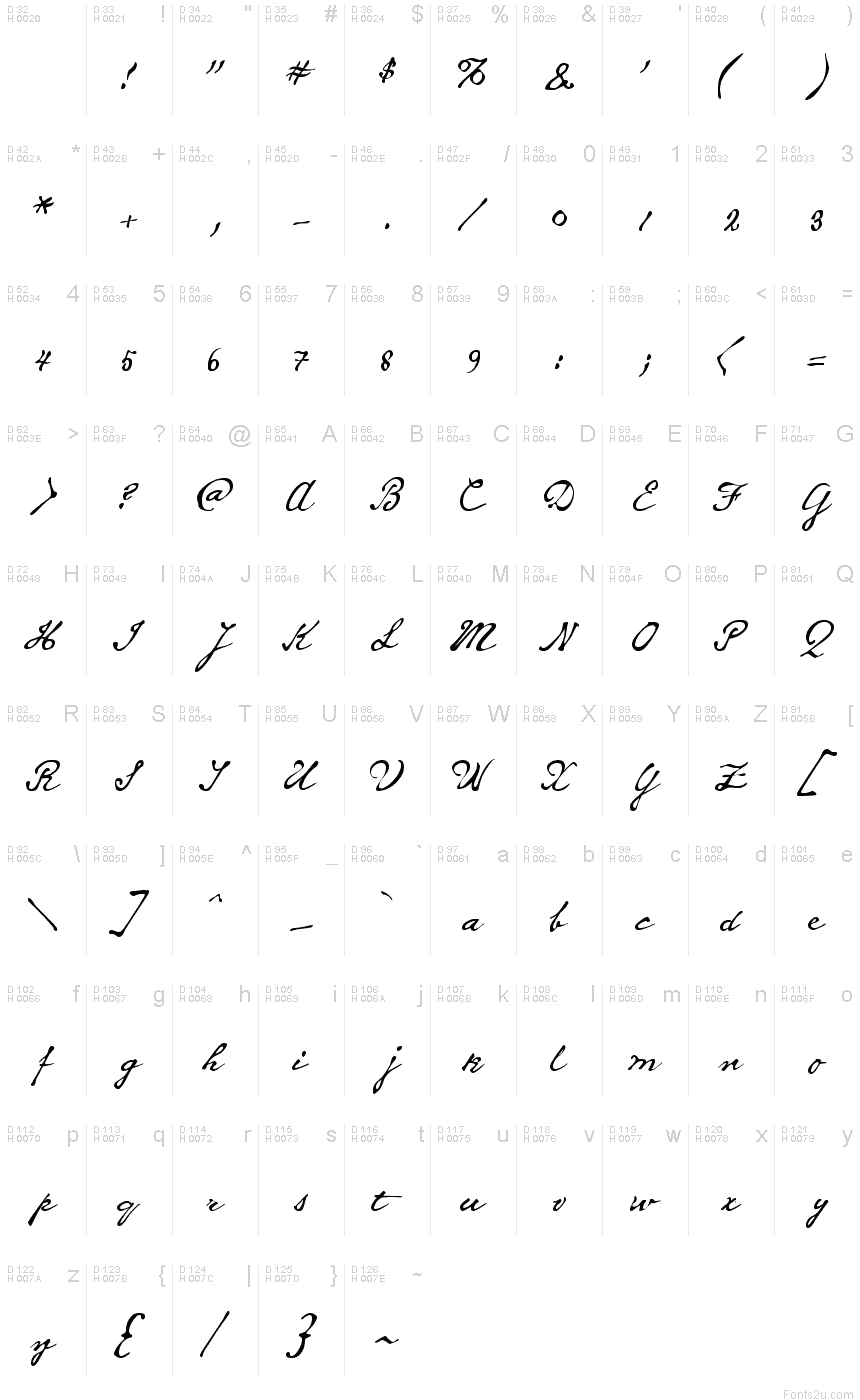
Whitechapel BB
Whitechapel BB è un font calligrafico scritto a mano gratuito di Nate Piekos, caratterizzato da tratti ampi e un ritmo equilibrato, simile a una firma. Le lettere si muovono tra curve larghe e raccordi rapidi e sottili, mentre i lunghi tratti di ingresso e uscita conferiscono alle parole un dinamico flusso orizzontale.
Questo font gratuito è perfetto per il branding di boutique, il packaging di prodotti beauty, la cancelleria per matrimoni, le copertine editoriali e i titoli cinematografici, dove un tocco personale è più efficace di una composizione formale. Utilizzalo per nomi, brevi titoli o citazioni; i generosi svolazzi hanno bisogno di spazio per espandersi, conferendo alla grafia un aspetto sicuro e non affollato.